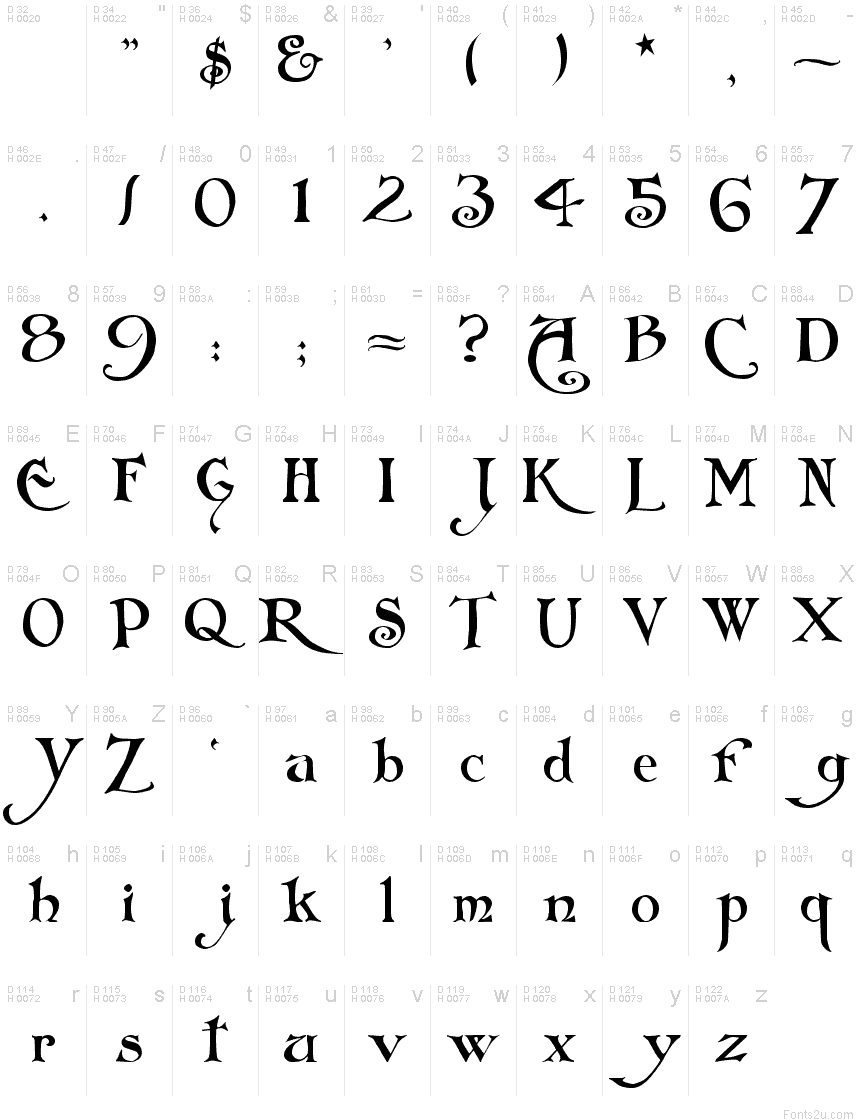
Folkard autorstwa Davida F. Nallego to bezpłatny, ozdobny krój pisma w stylu retro, który wygląda, jakby został wyjęty ze stron starej księgi baśni. Grube, nieregularne pociągnięcia, delikatne drżenie przypominające tusz i zamaszyste krzywe nadają każdemu słowu ręcznie wykonany, nieco mistyczny charakter – bardziej przypominający szyld karczmy lub czarodziejską księgę niż wygładzony plakat. Krój jest wyrazisty i ciemny, dzięki czemu krótkie frazy i nazwy zyskują mocną, nastrojową oprawę.
Z Folkard błyskawicznie nadasz odpowiedni klimat okładkom książek fantasy, podręcznikom do gier RPG, interfejsom gier, plakatom imprez historycznych, tematycznym menu czy projektom z magicznym motywem. Ten bezpłatny font najlepiej prezentuje się, gdy ma dużo przestrzeni w większych rozmiarach, w połączeniu z czystym krojem szeryfowym lub bezszeryfowym w tekście głównym, pozwalając Folkard przejąć rolę w nagłówkach i logotypach.